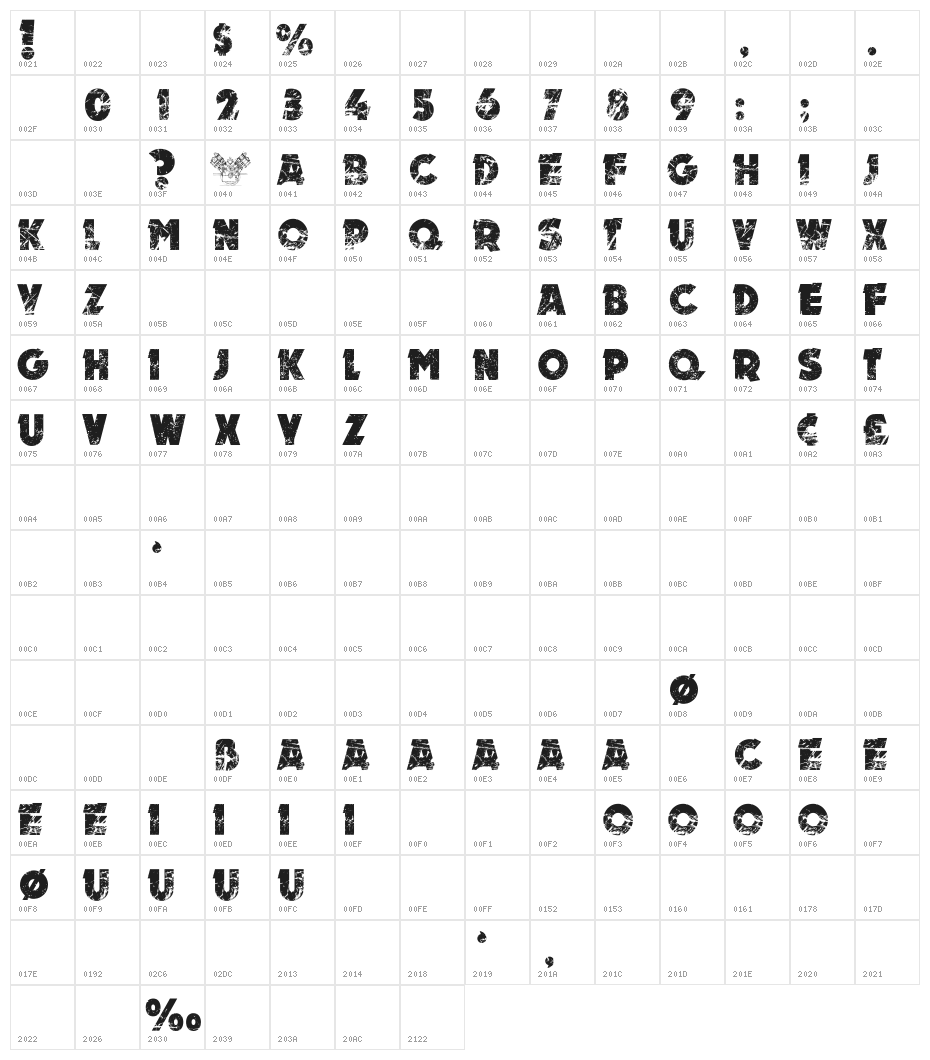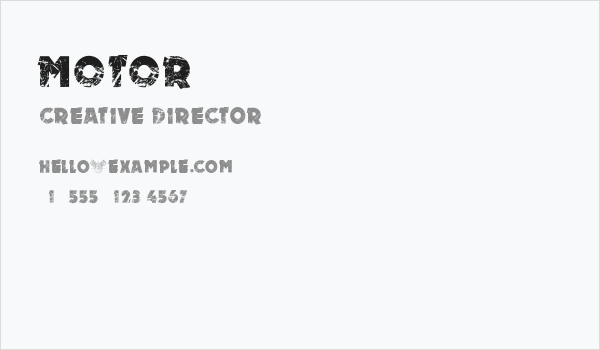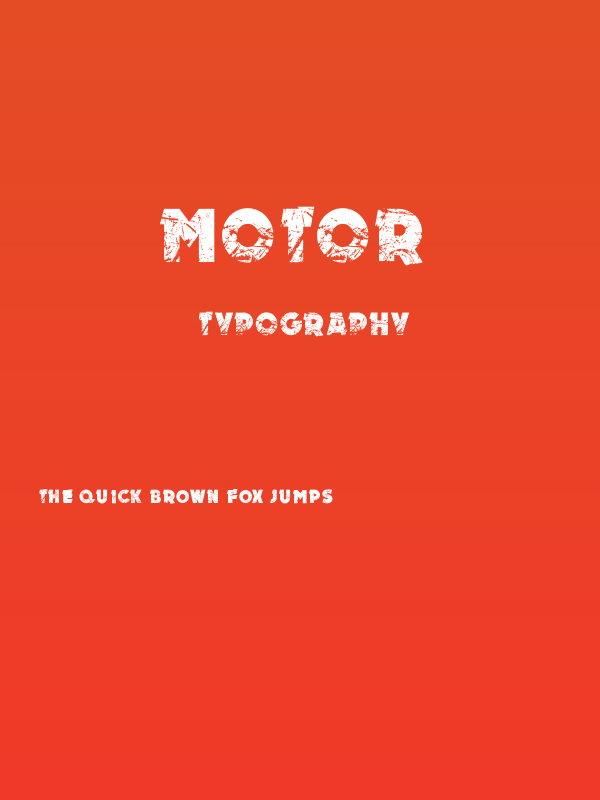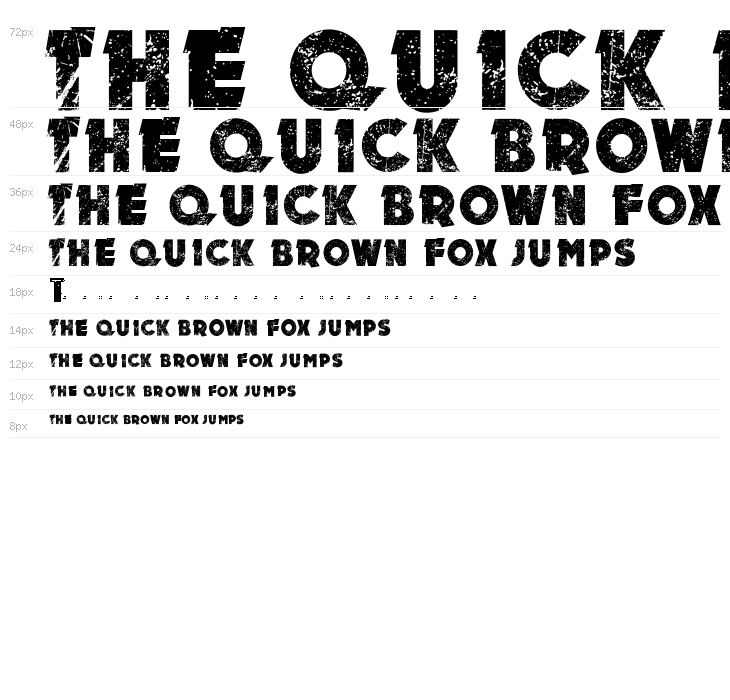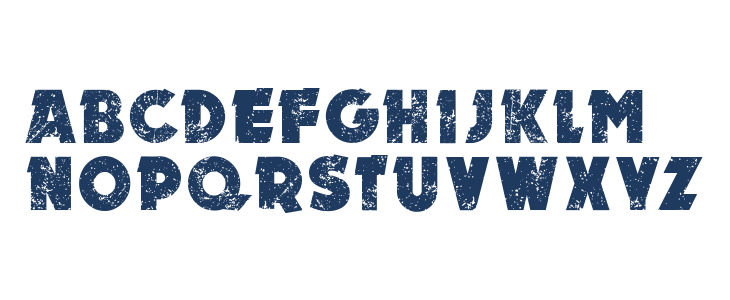
MOTOR Font
✎ Distorted Eroded
| النمط العام | Vintage |
| مشاريع مقترحة | Ideal for projects needing a strong, industrial feel, such as posters, logos, or branding for automotive or vintage-themed businesses. |